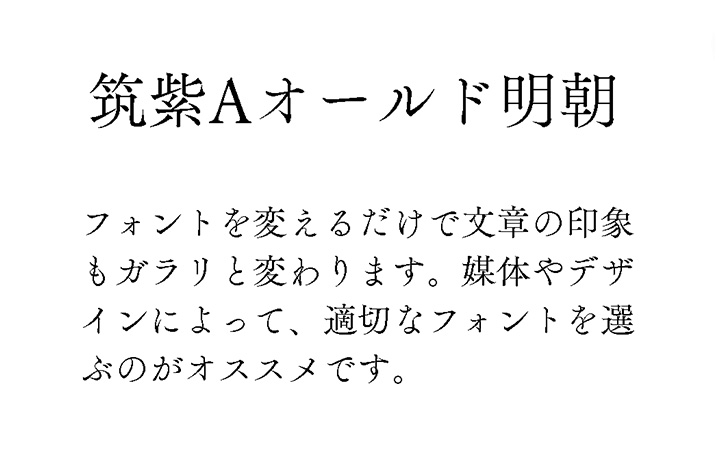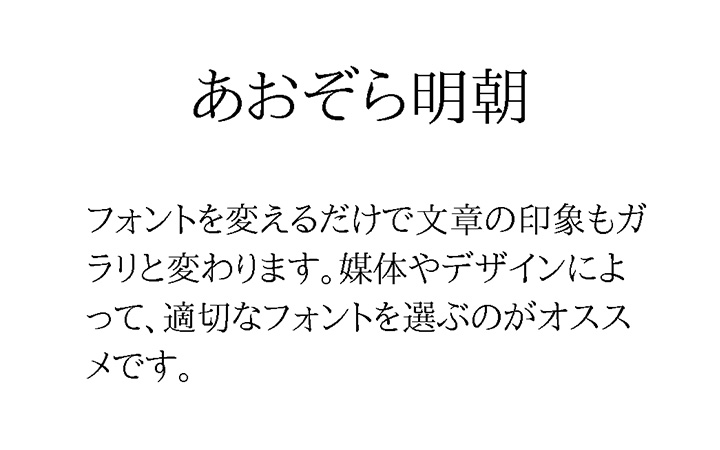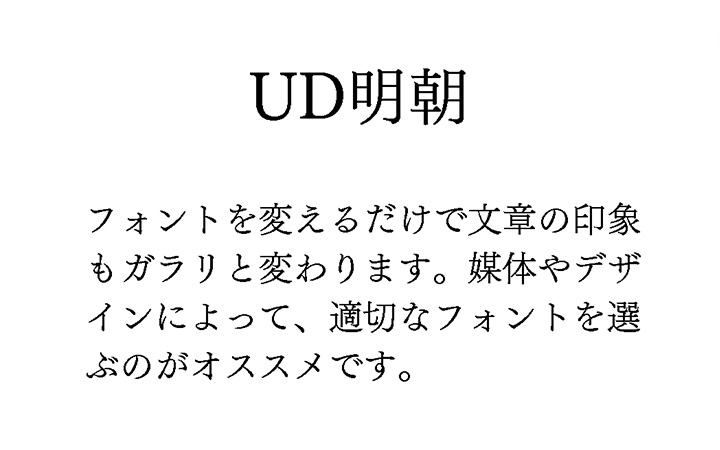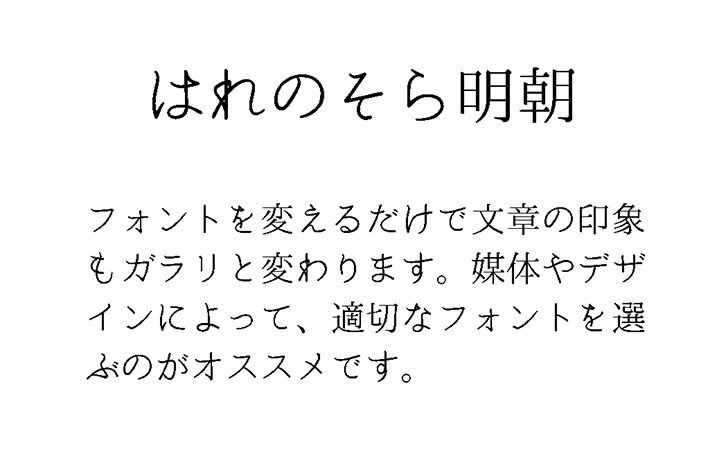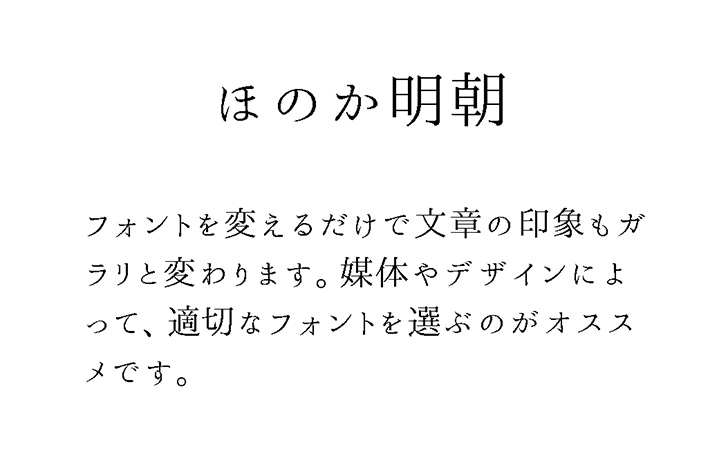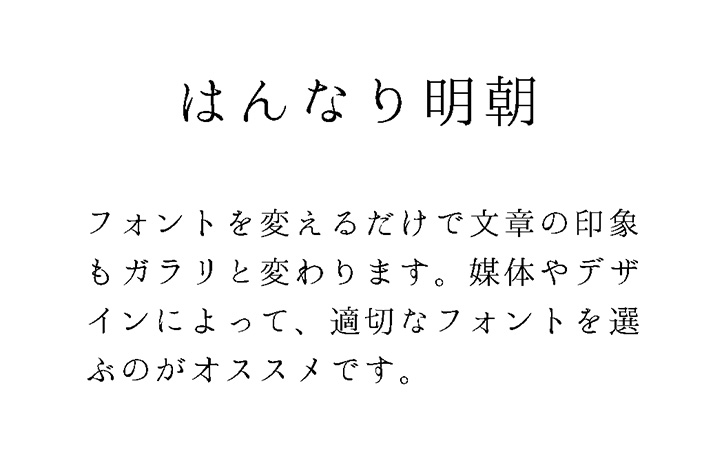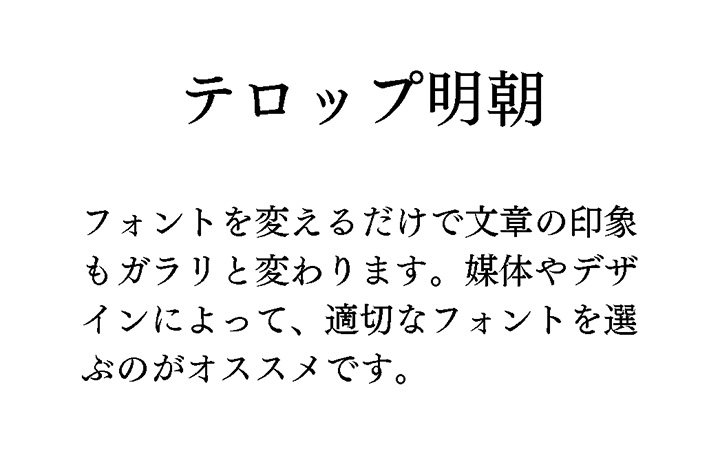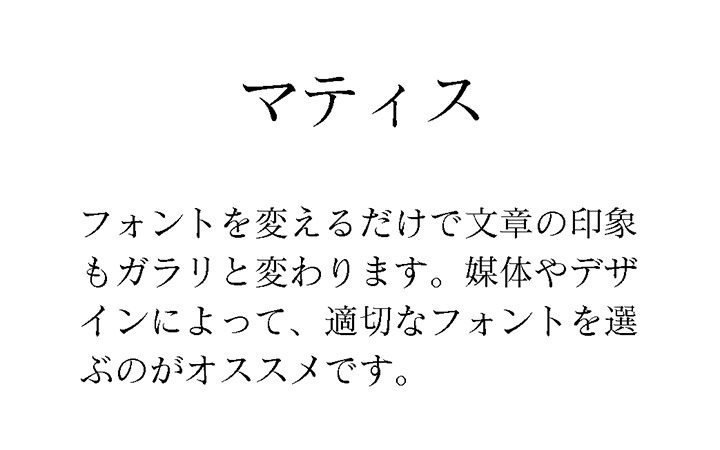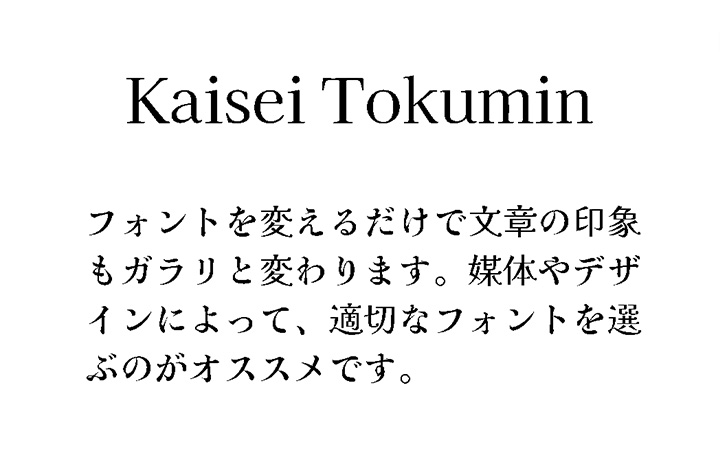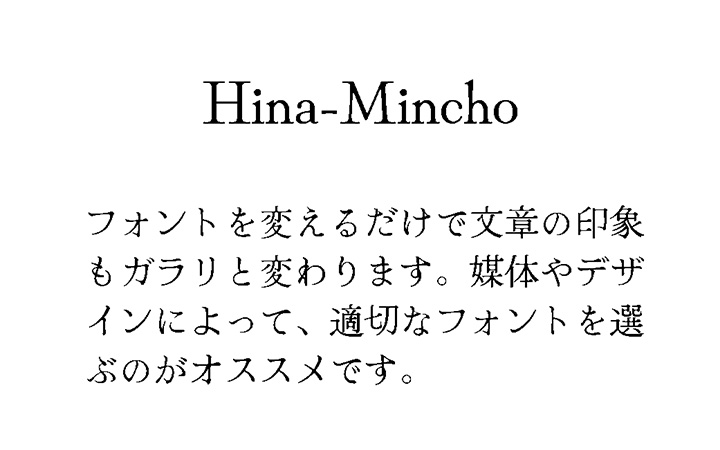
Canvaで使える日本語フォント:明朝
筑紫Aオールド明朝
| フォント名 | 筑紫Aオールド明朝 |
| ポイント | 文字のハネ・ハライが特徴的で、文章にした時もしっかりと視認できるため、紙媒体との相性が抜群のフォントです。 |
あおぞら明朝
| フォント名 | あおぞら明朝 |
| ポイント | 線の強弱と、柔らかさによって、使いやすい明朝体の一つ。サイズを大きくすればインパクトも出せます。 |
UD明朝
| フォント名 | UD明朝 |
| ポイント | 誰もが見やすいフォントとしてユニバーサルデザイン(UD)をコンセプトに作られたフォントなので、柔らかさがありながら見やすさも担保されている、非常に使いやすい明朝体で飽きが来ません。 |
花園明朝
| フォント名 | 花園明朝 |
| ポイント | 線が細め目の明朝体ですが、文章にしたときも見やすさが維持されている。細さを活かして強弱も付けられているため、使いやすい明朝体です。 |
はれのそら明朝
| フォント名 | はれのそら明朝 |
| ポイント | 部分部分で筆記体のように文字内で線が繋がっており、特徴的な角丸の明朝体。ゆったりした印象で女性らしさも感じられます。上品さを加えたいときにオススメのフォント。 |
ほのか明朝
| フォント名 | ほのか明朝 |
| ポイント | 文字一つ一つが柔らかな曲線で作られています。ひががな・カタカナと比べて漢字が若干大きめなので癖はありますが、優しい気持ちにさせてくれるフォント。 |
はんなり明朝
| フォント名 | はんなり明朝 |
| ポイント | あえて曲線が強められ、そこに手書き感がミックスされて、上品な中に可愛らしさを感じるフォントです。 |
テロップ明朝
| フォント名 | テロップ明朝 |
| ポイント | ベースとなる明朝体の線幅を少し太目にして、ディスプレイ越しでも文字がハッキリと分かるよう作られたフォントです。 |
マティス
| フォント名 | マティス |
| ポイント | 太さの強弱が付けられながら、少し丸みのある明朝体。カタカナ・ひらがな・漢字の差異がほとんどなく、すべて同一のフォントとして認識できる。読みやすさも考えられています。 |
Kaisei Tokumin
| フォント名 | Kaisei Tokumin |
| ポイント | 線を太めにする部分をあえてつくり、線の強弱によってオシャレ感をUPさせているフォント。 |
Hina-Mincho
| フォント名 | Hina-Mincho |
| ポイント | 丸みを強調させており、全体的に円を感じる文字になっています。優しさや品を感じさせるフォント。 |
Canvaで使える日本語フォント:明朝 + 手書き
New Tegomin
| フォント名 | New Tegomin |
| ポイント | 全て手書きされて作られたフォントで、他のフォントにはない書体になっています。一つずつの文字の視認性が高く、長い文章にしてもしっかりと読める。 |
Canvaで使える日本語フォント:手書き風
Potta One
| フォント名 | Potta One |
| ポイント | 筆文字風で文字もかなり崩していますが、それがまた味のあるテイストで仕上げてあり、使い手の心をワクワクさせるフォント。このフォントでアルファベットを使えば、墨だまりなどが強調されるので、筆で可愛らしさを表現できます。 |
レゲエ
| フォント名 | レゲエ |
| ポイント | 文字のはらう部分をあえて細くし、その他を太めることで、強弱の差を大きくしてダイナミックを感じるフォントになっています。 |
吐き溜
| フォント名 | 吐き溜 |
| ポイント | 凸凹を強調させたり、あえて汚さを演出することで、怖さを出しているフォント。画数の多い漢字にしても視認性は担保されているため、大き目にも使える。 |
851チカラヅヨク
| フォント名 | 851チカラヅヨク |
| ポイント | 文字の先端部分をそれぞれモゾモゾさせている特徴的なフォント。手書き風らしく動きがあるため、見出し・キャッチコピーなどで使うのもオススメです。 |
Canvaで使える日本語フォント:極太
ラグラン